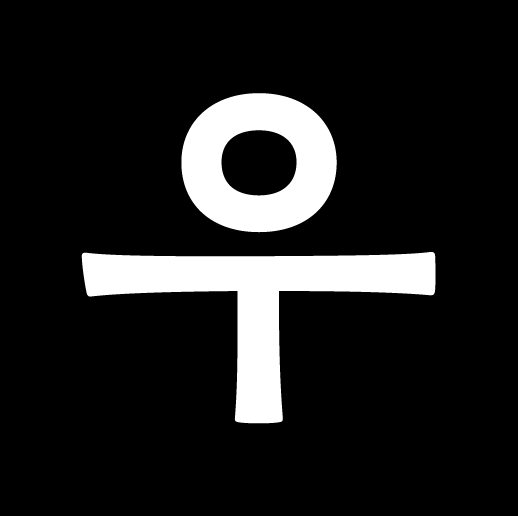
우이예 우이예는 동아시아 문자 전통을 재해석하여 독특한 표정의 글자들을 만듭니다. 위예진의 폰트 스토리 동아시아 활자 디자이너, 우이예의 「죽순」 제작기 한글꼴창작지원사업 선정작, 「죽순」의 제작 비하인드와 베타 출시 소식까지 만나보세요! 폰트 30px 우이예 죽순 Beta 1종 1